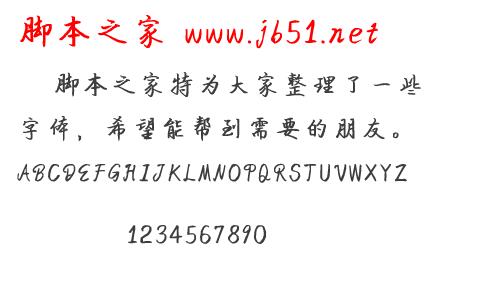
方正手跡-半曉該字在字形結(jié)構(gòu)上,比較接近啟體,結(jié)體嚴(yán)謹(jǐn)。但在筆畫(huà)上,采用較為均勻的粗,在讀者視覺(jué)感受上,會(huì)更加舒適。 適用于文藝類(lèi)的書(shū)刊、品牌廣告和產(chǎn)品包裝設(shè)計(jì),以及社交網(wǎng)絡(luò)的個(gè)性化用字。